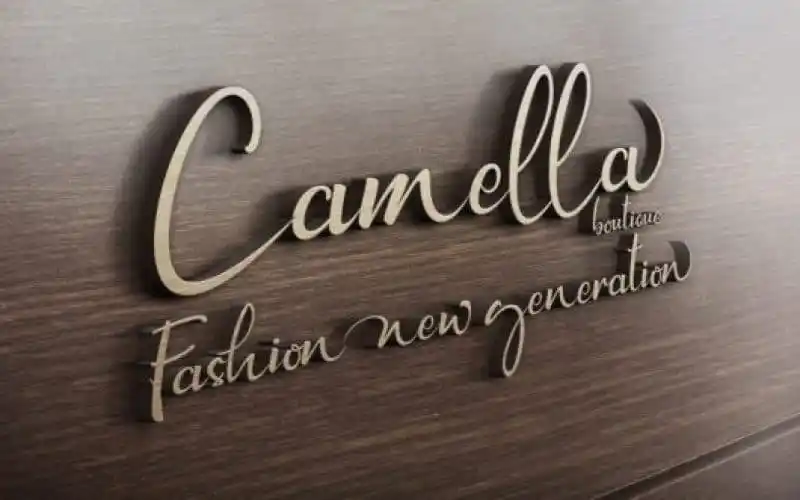
Newyorka Night Script Font – Download Grátis
A Newyorka Night Script Font é uma escolha perfeita para aqueles que buscam uma mistura única de elegância moderna e autenticidade no seu trabalho. Dedicada a designers que desejam adicionar um toque autêntico a seus designs, seja em cartões de festa, postagem social ou arte de papelaria, esta fonte é ideal para criar elementos únicos e criativos. Criada pelo designer Agus Diantoro, a Newyorka Night Script Font traz uma sensação moderna e sofisticada aos seus projetos gráficos. Com seu estilo elegante e autêntico, ela se destaca como um fonte de texto para uso em qualquer projeto que deseje um toque de classe e originalidade. Este é o ideal para quem busca criar um design fresco e moderno sem perder a essência pessoal e única da sua arte. Sua simplicidade criativa pode transformar até os mais simples projetos em obras de arte singulares, tornando-a uma fonte indispensável no seu arsenal criativo.